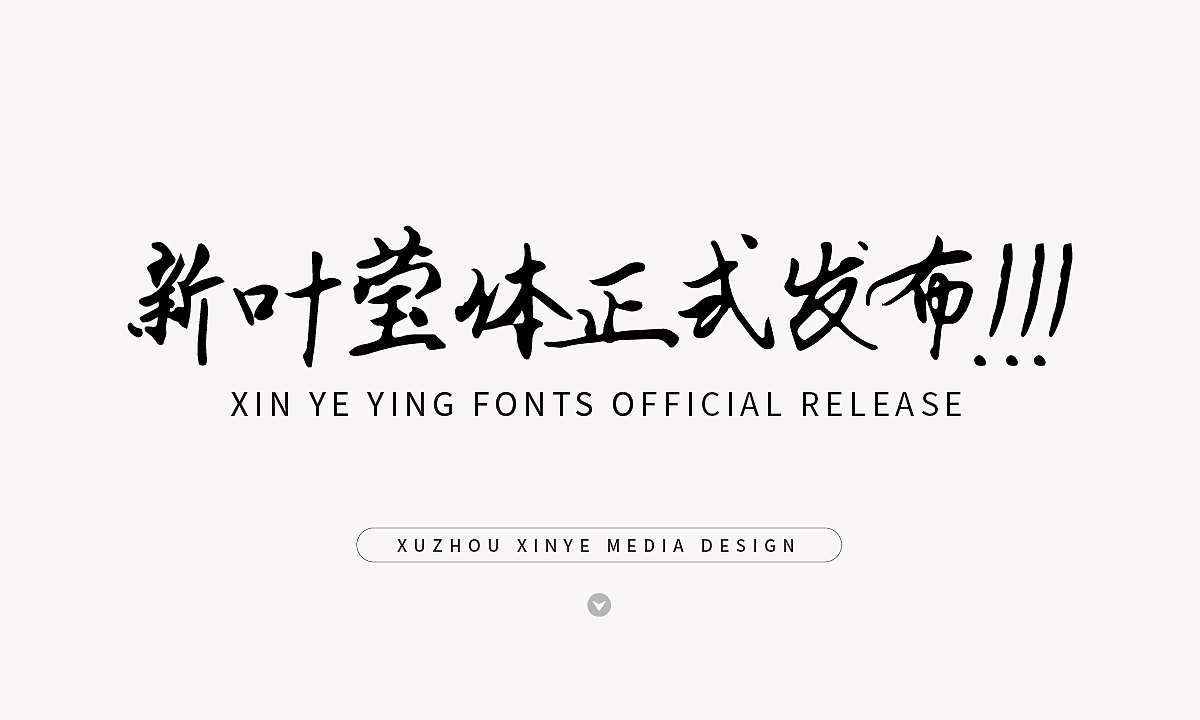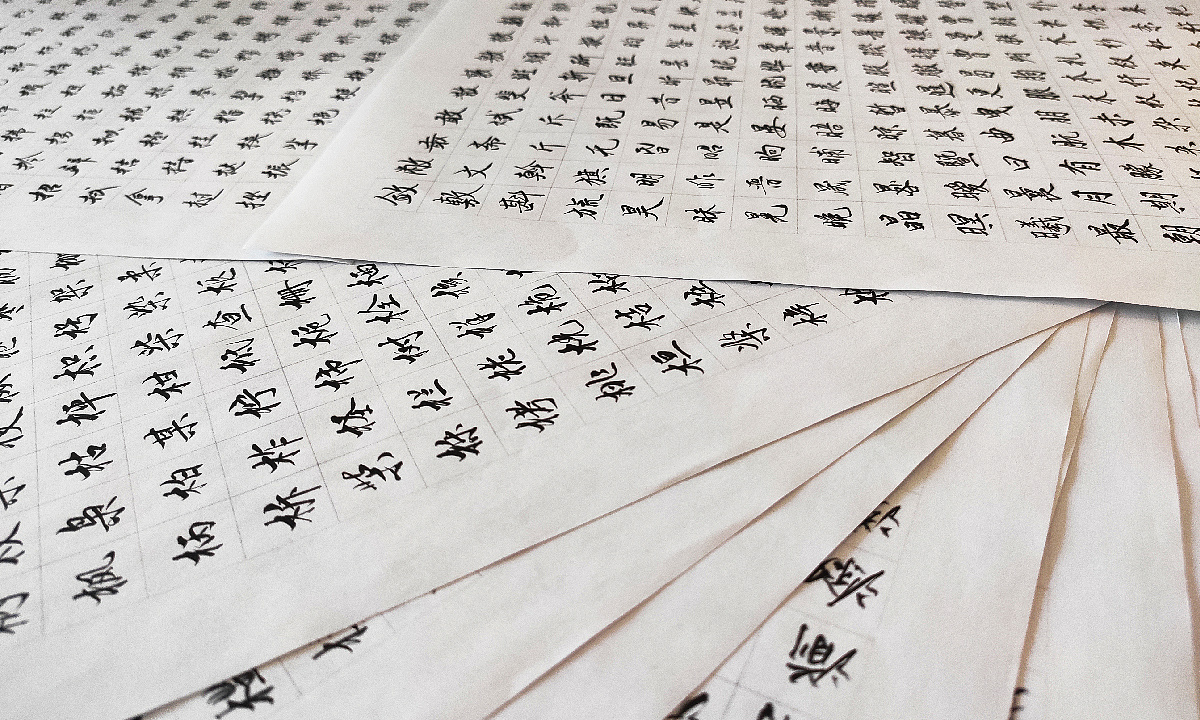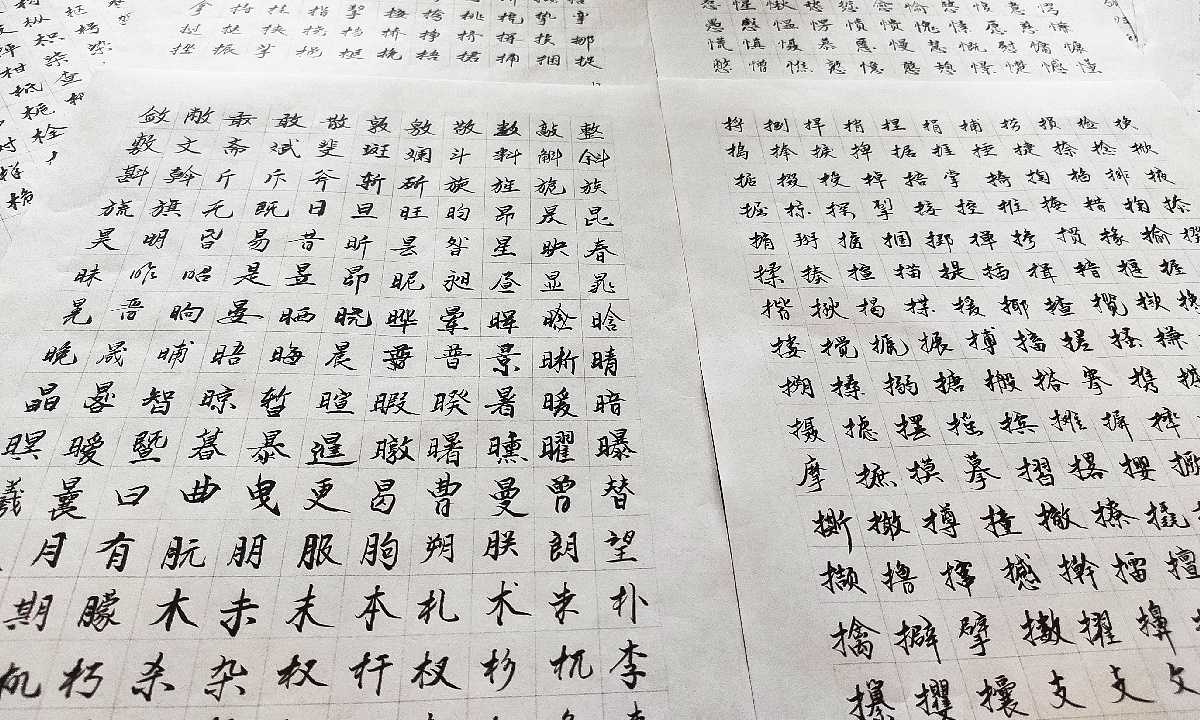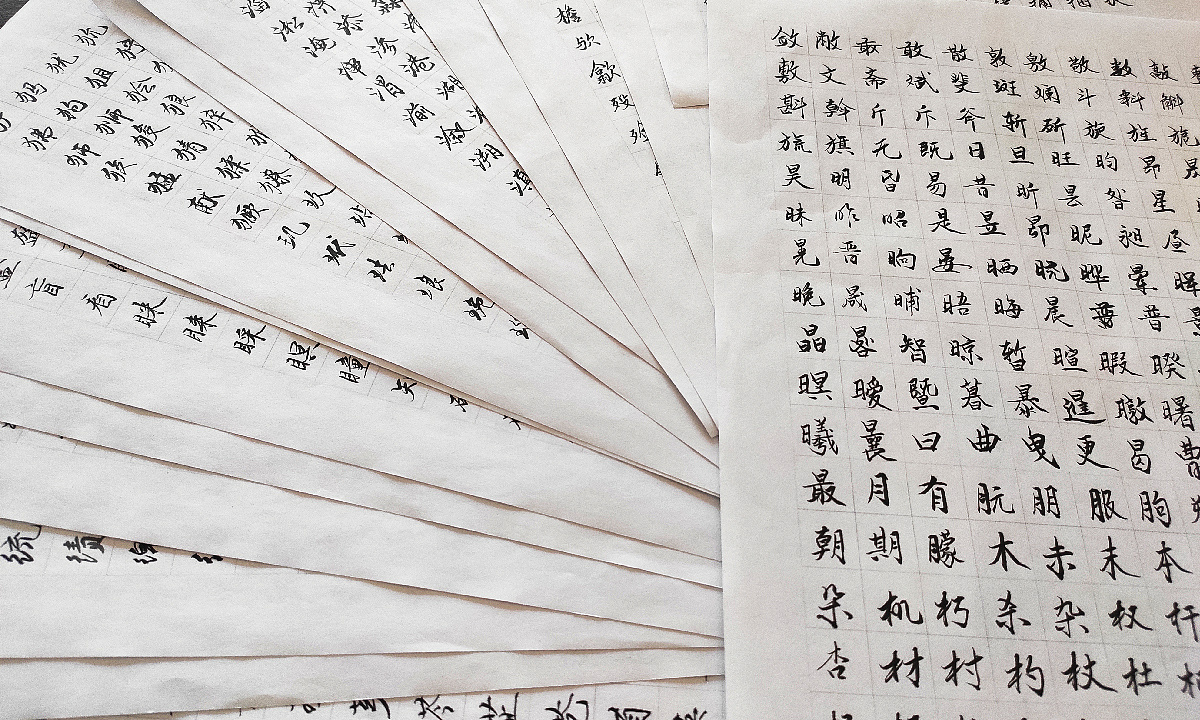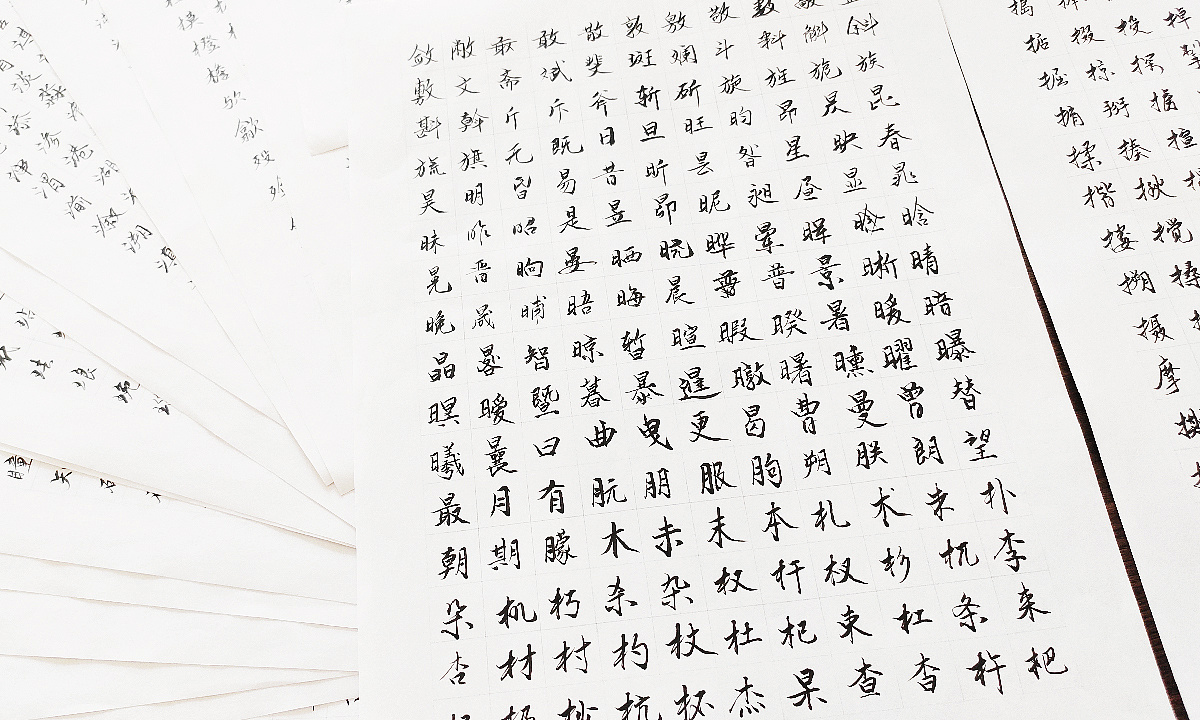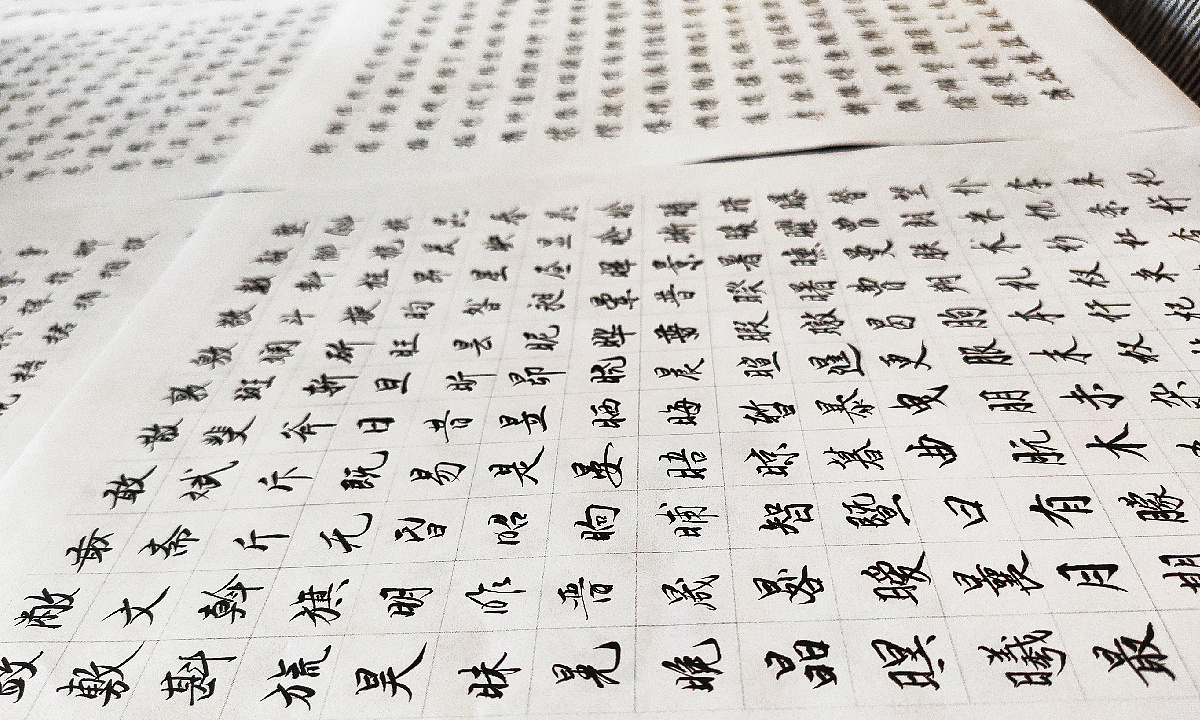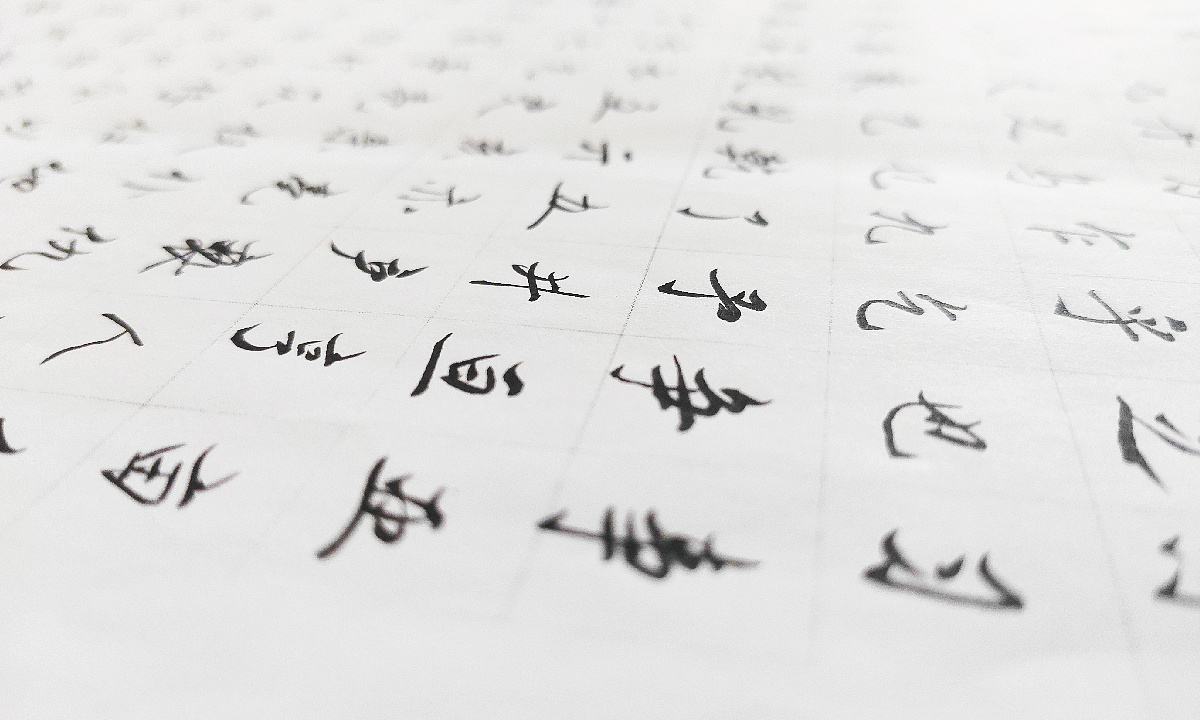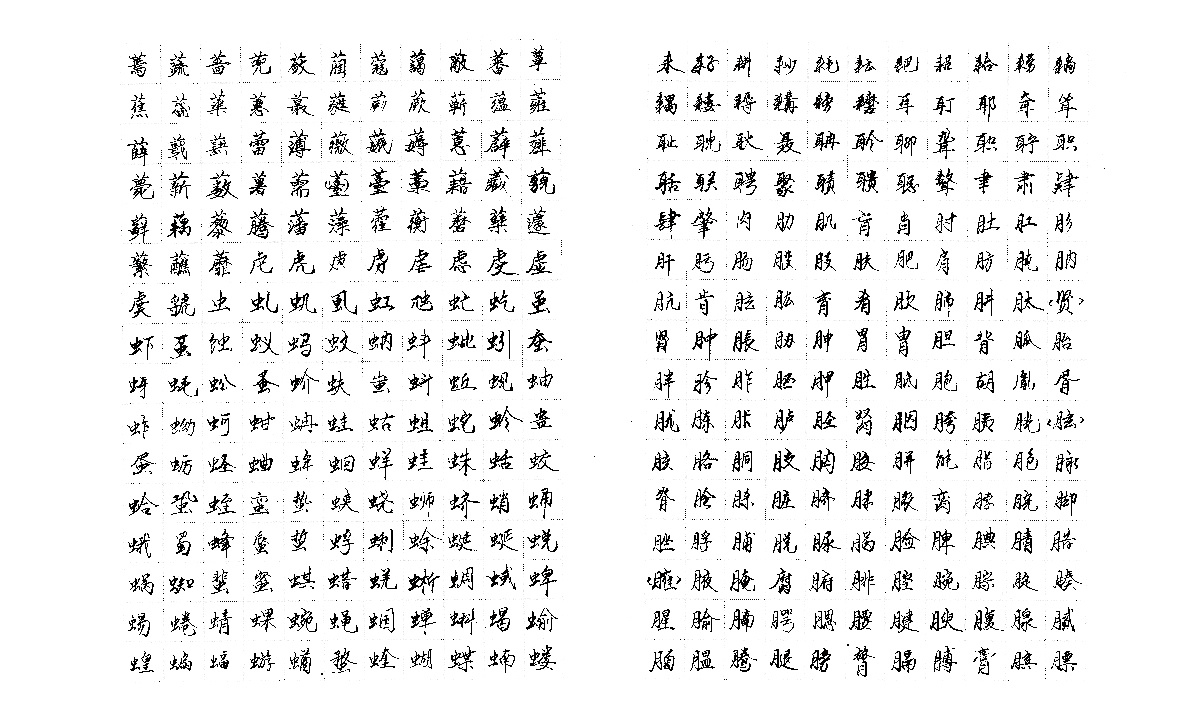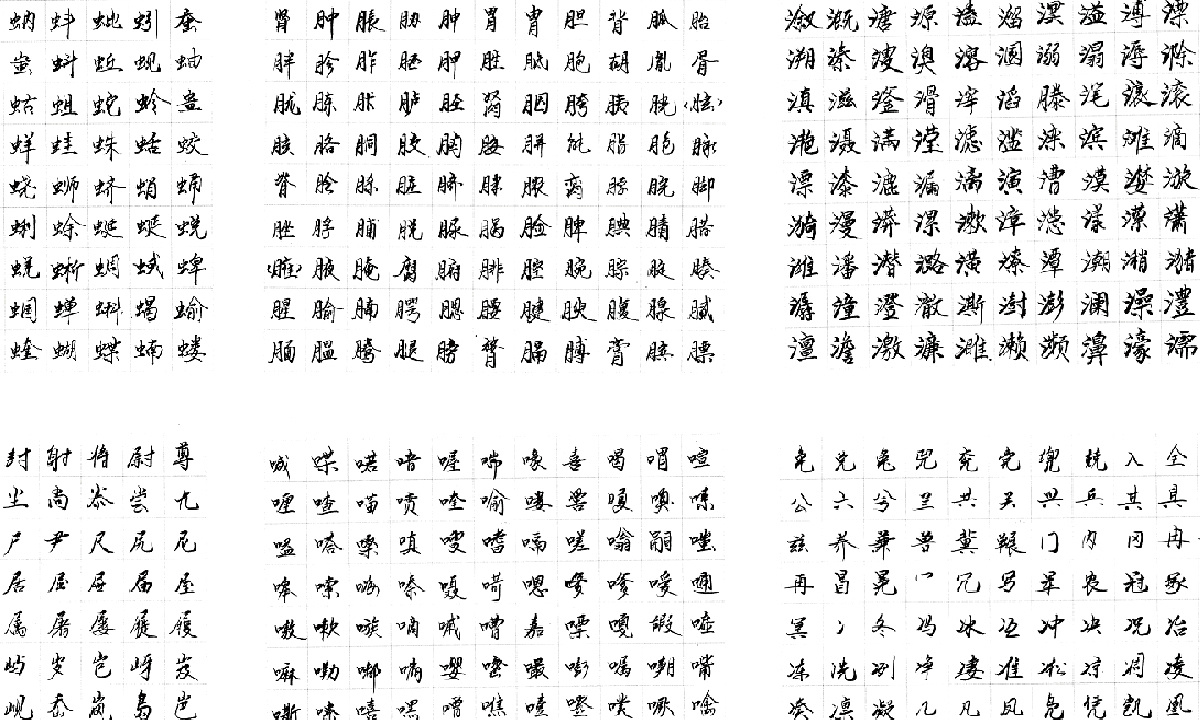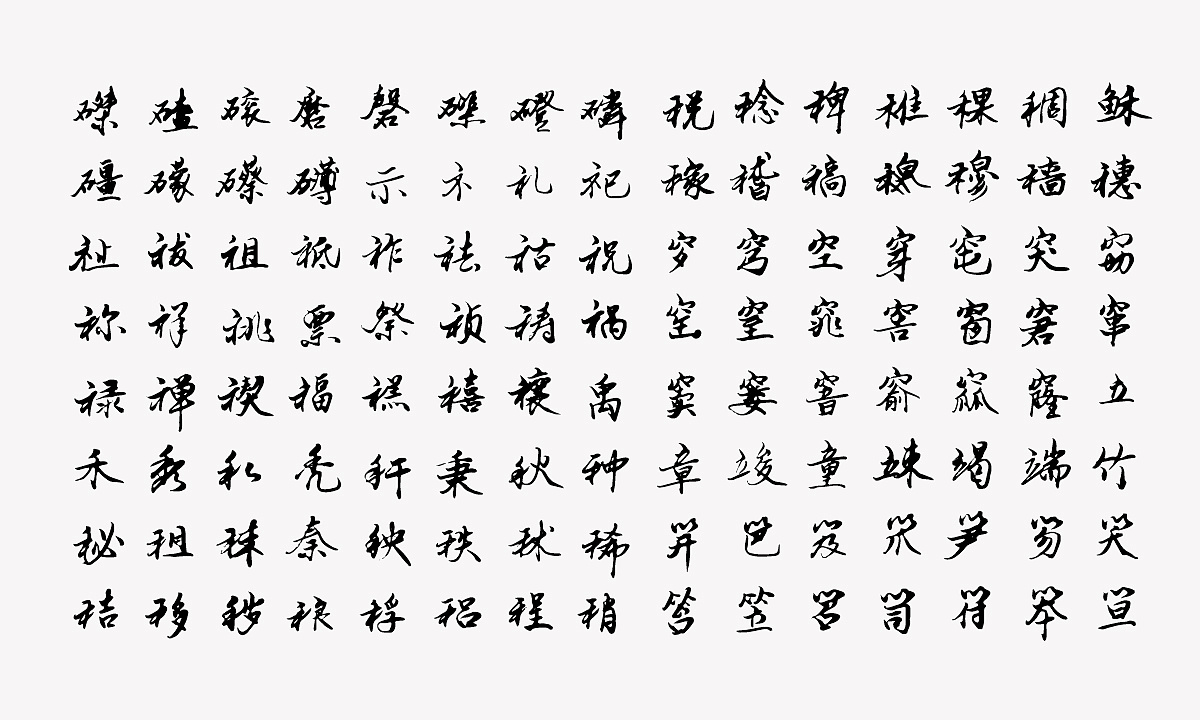
字體名稱: 新葉瑩體
新葉瑩體
這副字體看上去溫柔而遒勁,一筆一畫之間抒寫著一種外柔內剛的堅毅,橫豎撇捺之間氤氳著一絲絲的靈動,像陽光下的玉石散發著淡淡的光彩,溫和而不刺眼,寓意為“瑩”,這便是字體名字的由來了!
秀逸勻整的筆畫橫陳在每個文字間,透露著一種陰陽和諧之美,每一個文字的筆畫都柔和平緩,避免了太過鋒利,就像做人一樣要磨平棱角處事,但也要保留自己的特色一樣。
我們要告別千篇一律的生活,我們要穿著我們喜歡的衣服,吃著喜歡的美食,用著特別的字體發著微信、發著簡訊給特別的人,傳遞特別的心意。愿新葉瑩字體陪你度過往后余生!
字體名稱:新葉瑩體
字庫字數:簡體+符號共計7123字
字體風格:柔和而堅毅
適用范圍:品牌標志、廣告、影視綜藝、包裝、漫畫等